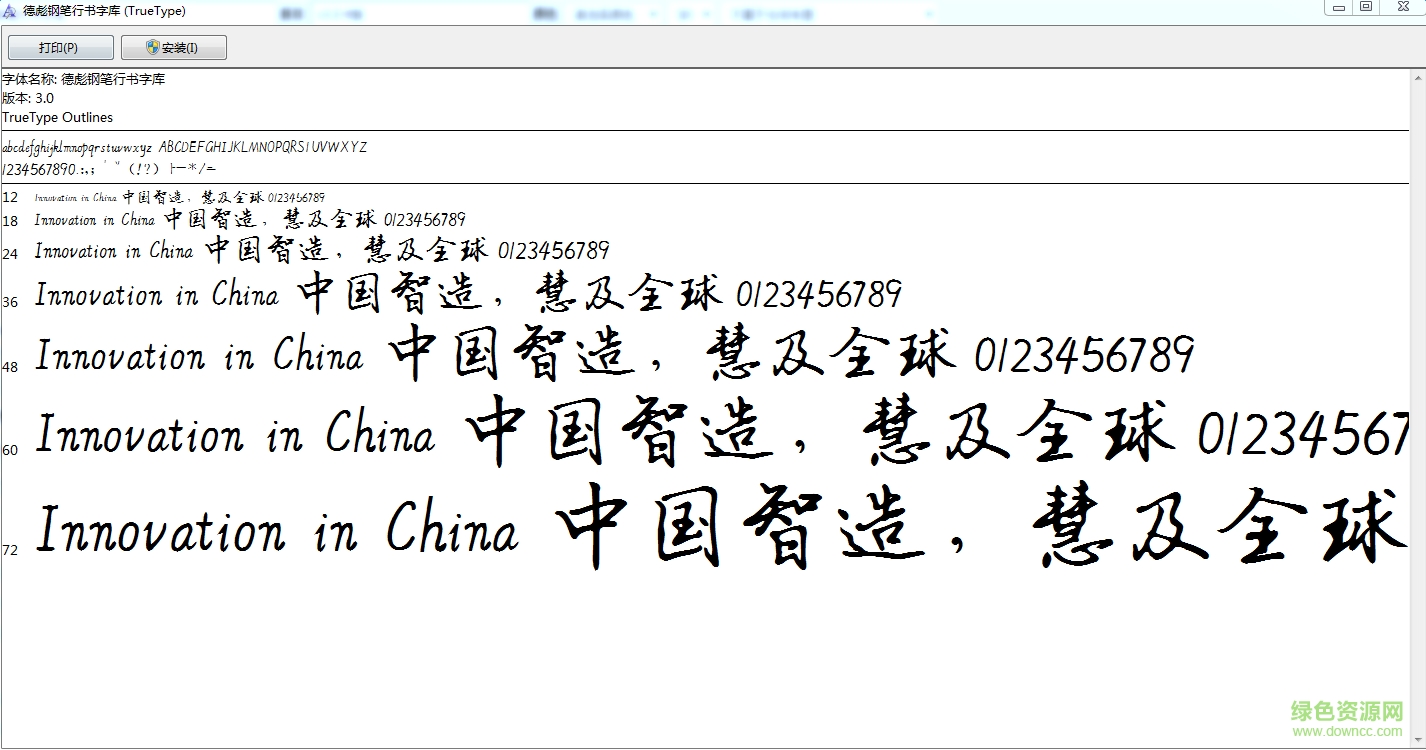
lidebiao xing 2.0字體又叫德彪鋼筆行書字庫(kù)2.0,該字體疏密得體,俊逸自如,點(diǎn)畫流暢,字里行間縱逸灑脫,實(shí)用性強(qiáng),歡迎大家免費(fèi)下載!
【大小相兼】
就是每個(gè)字呈現(xiàn)大小不同,存在著一個(gè)字的筆與筆相連,字與字之間的連帶,既有實(shí)連,也有意連,有斷有連,顧盼呼應(yīng)。
【收放結(jié)合】
一般是線條短的為收,線條長(zhǎng)的為放;回鋒為收,側(cè)鋒為放;多數(shù)是左收右放,上收下放,但也可以互相轉(zhuǎn)換,不排除左放右收,上放下收。
【濃淡相融】
行書書寫應(yīng)輕松、活潑、迅捷,掌握好疾與遲、動(dòng)與靜的結(jié)合。墨色安排上應(yīng)首字為濃,末字為枯。線條長(zhǎng)細(xì)短粗,輕重適宜,濃淡相間。和草書差不多,但沒那么草。